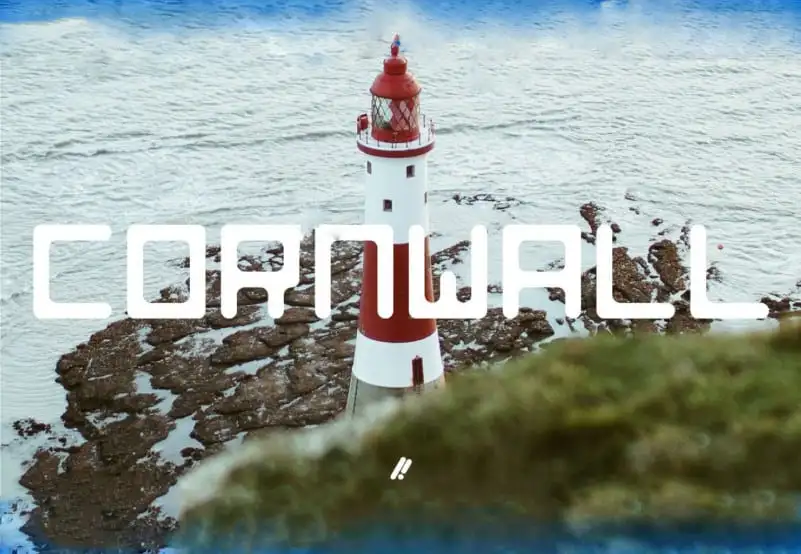
Cornwall Display Font é uma nova fonte de exibição totalmente gratuita criada pelo designer Harrison Luke. Essa fonte tem uma aparência robusta do tipo sans-serif, que combina elementos rígidos de tipografia baseadas em grades com cantos redondos e divertidos. É perfeito para qualquer projeto visual que deseja um toque moderno e versátil sem sair da linha. Seja para nomes de marca, banners ou editoriais digitais, Cornwall Display Font traz uma cara única ao seu design. Com sua ampla gama de caracteres, incluindo letras maiúsculas, números, pontuação e símbolos, pode ser facilmente integrada em qualquer tipo de projeto gráfico. Experimente alegria e simplicidade na medida exibição para criar designs que chamem atenção e se destacam nas plataformas digitais atuais.